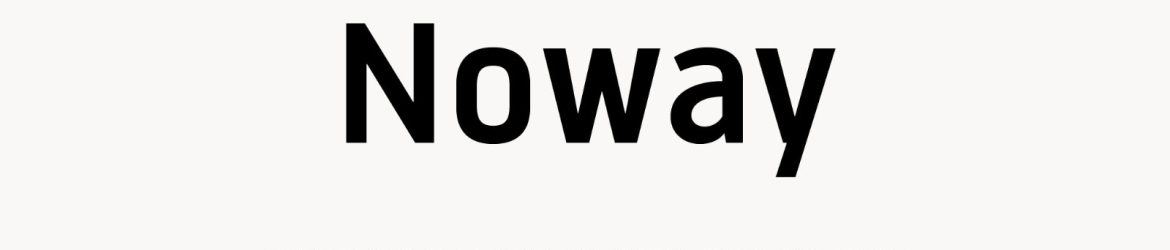
O Noway Corporate Signage Typeface é uma fonte desenvolvida para atender às necessidades de identidade visual de empresas e empreendimentos em espaços de alto perfil, como aeroportos. Sua origem é na Londres Luton Airport, onde foi concebida para atender às necessidades de identificação e comunicação visual. O Noway fonte inclui uma família de 10 pesos: Espinhos, Ligeiro, Normal, Médio, Bold e Itálico, além de uma coleção de 159 ícones para todos os tipos de utilizadores possíveis. O Noway foi projetado para atender a uma ampla gama de necessidades, incluindo marcas de marca, embalagens, editoriais, indicação de caminhos e identificação visual em espaços de uso comum. Este recurso gráfico é igualmente adequado para design web e ecrã. A sua simplicidade e elegância permitem que seja adaptado a muitos estilos de design, tornando-o uma ferramenta de design versátil e profissional. O Noway Corporate Signage Typeface é a escolha perfeita para quem procura um recurso gráfico robusto, versátil e de alta qualidade para a sua marca.